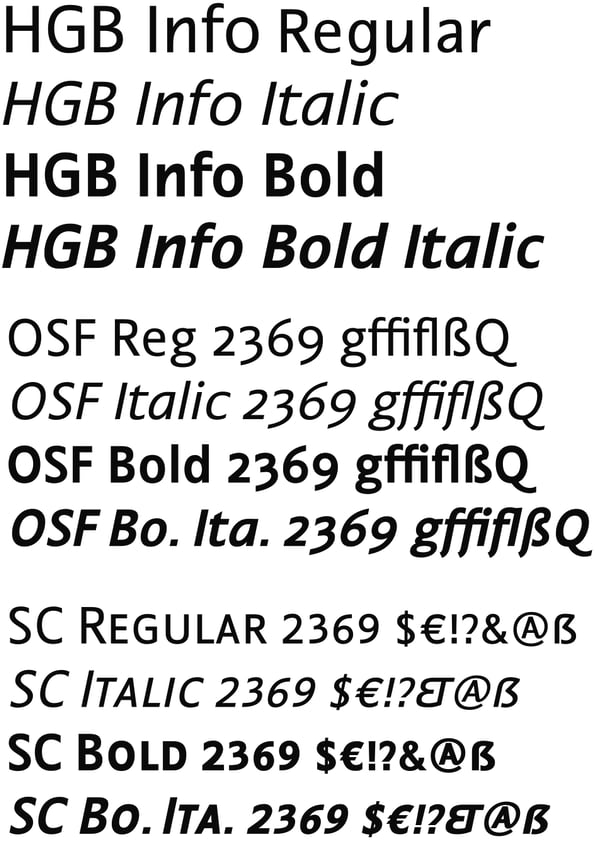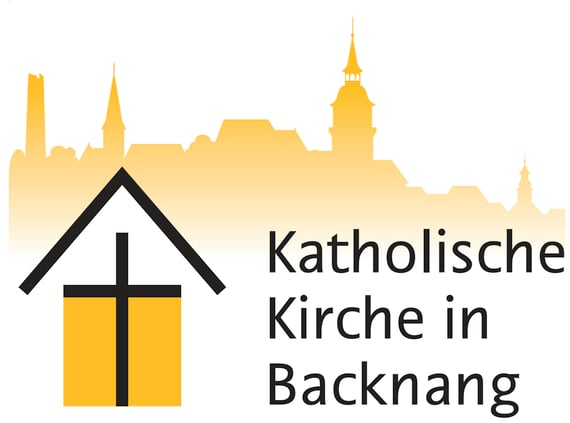
HGB Info
Diese Display-Version der Nautilus Monoline ergab sich bei der Arbeit am Erscheinungsbild der Gemeinde Weissach im Tal. Die Anforderung war eine kompakte Außenform für den Schriftzug, deshalb wurden die Ober- und Unterlängen gekürzt. Der zweite Unterschied ist die etwas breitere Buchstabenfom und die senkrechten Abschlüsse der An- und Abstriche. Dies führt dazu, dass zwar eine Verwendung für längere Texte nicht mehr empfehlenswert ist, dafür wirkt diese Form besonders gut in großen Graden und bei wenig Text. Die Gemeinde Weissach im Tal hat seit 2018 ein neues Erscheinungsbild ohne die Hausschrift. Dafür wird diese jetzt für die »Katholische Kirche in Backnang« benutzt.